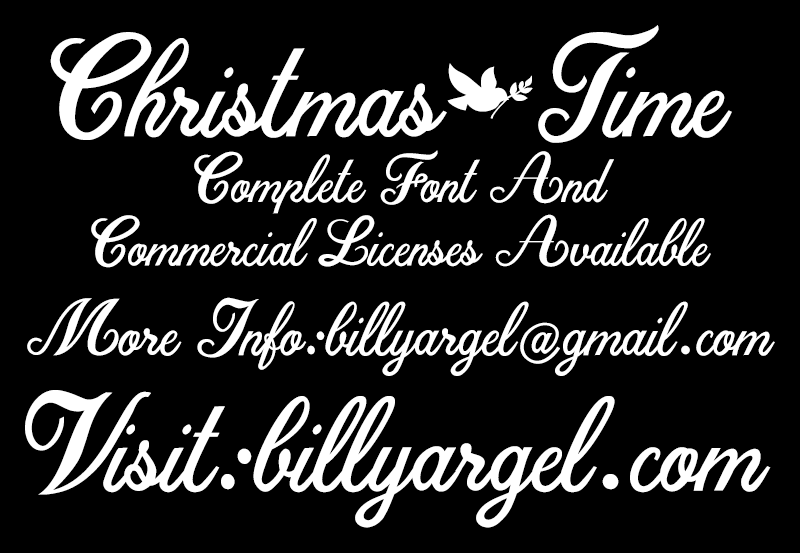
Christmas Time Typeface – Download Grátis
Aqui está uma versão para o português do Brasil, com 2 parágrafos curtos, descrevendo a fonte ‘Christmas Time Typeface’ em um tom informativo e convidativo: A fonte ‘Christmas Time’ é perfeita para aqueles que procuram imprimir mensagens carinhosas durante o natal. Desenvolvida pelo designer Billy Argel, ela destaca-se com linhas elegantes e uma tipografia artesanal ideal para uso em cartões de Natal ou postais. Ideal tanto para uso pessoal quanto comercial, a fonte oferece um toque especial na hora de personalizar mensagens que se tornam lembranças memoráveis. Seja para enviar um desejo de feliz natal aos seus amigos e familiares através de uma carta personalizada, ou para imprimir cartões de Natal com os sentimentos mais singelhos, ‘Christmas Time Typeface’ é perfeita. A fonte está disponível tanto em versão completa quanto em versão gratuita para uso pessoal, disponível para download na página do designer, www.billyargel.com. Para qualquer consulta adicional ou compra, você pode entrar em contato com o designer através de seu e-mail: